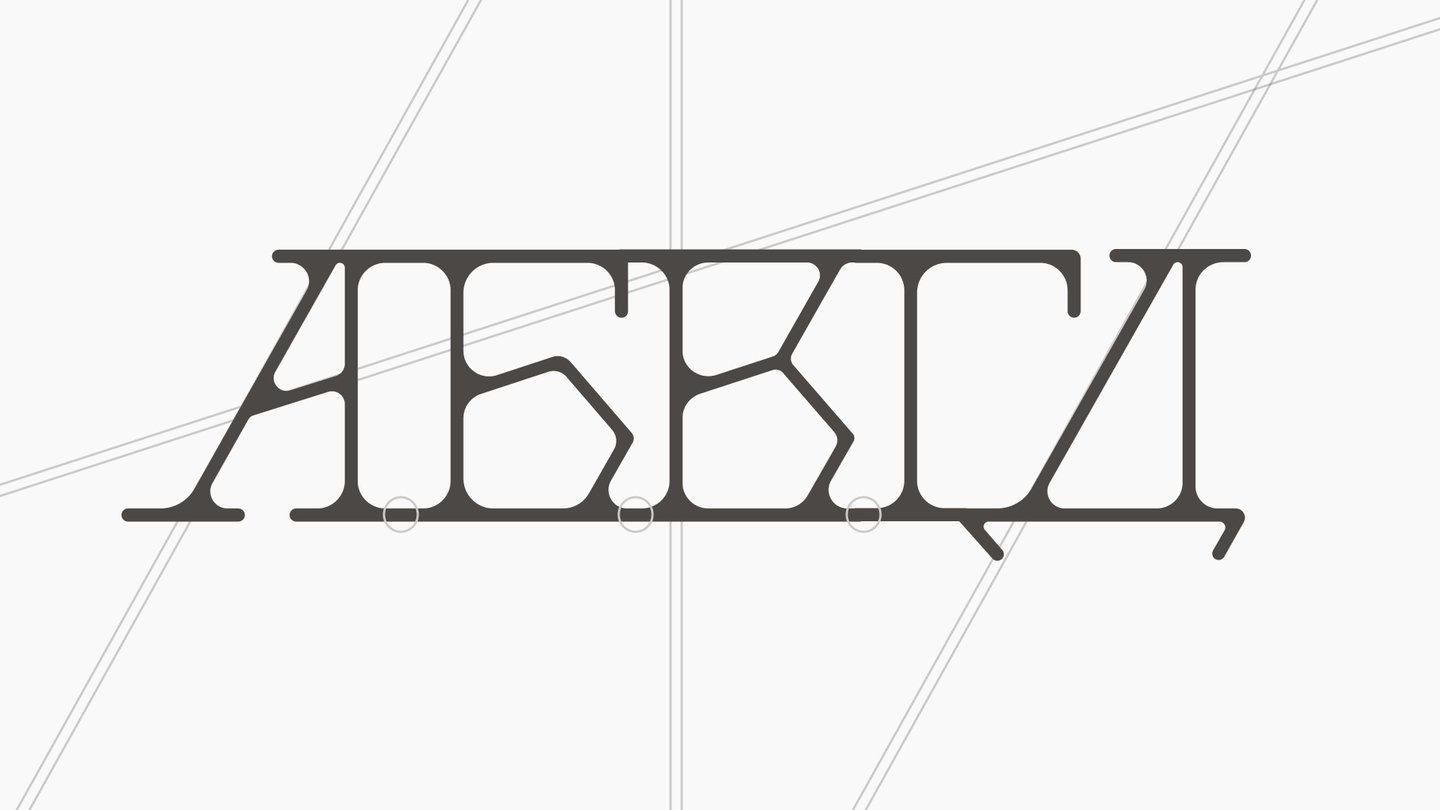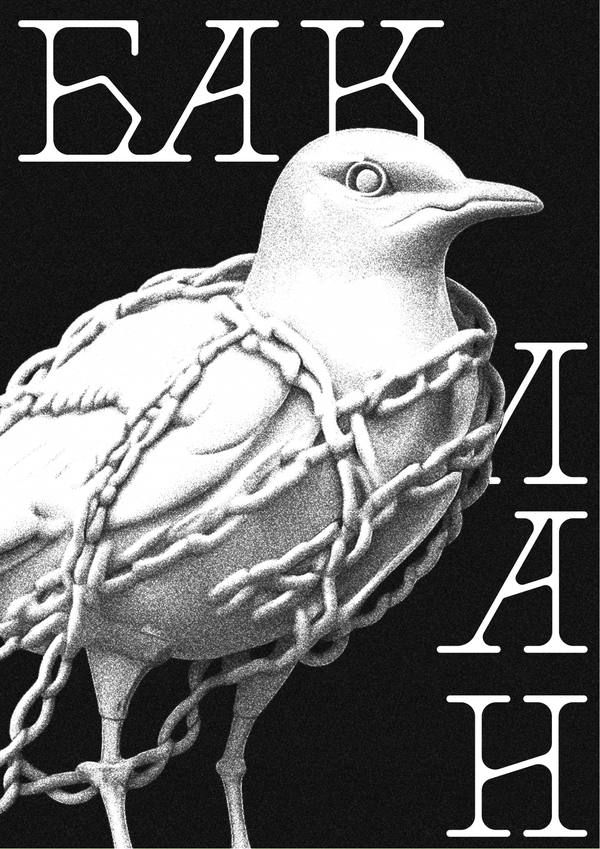
BAKLAN FONT
Baklan — причудливый акцидентный unicase-шрифт с тонкой пластикой, вдохновлённой формой и подвижностью суставов бакланов
шрифт строится на залипании букв и нарушенном ритме. сильные наклоны и «упавшие» перекладины создают ощущение нестабильной, живой формы
Шрифт может подойти для нишевых проектов, Y2K-эстетики и экспериментальных визуальных систем, хорошо работает с массивными обводками и контрастными приёмами